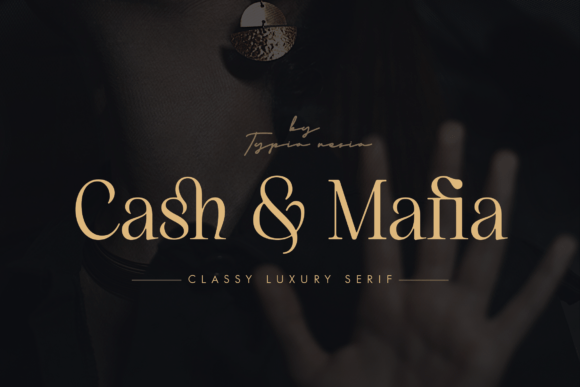
Cash and Mafia
Cash and Mafiaのような高品質の素材をお探しの場合、このプレミアムパッケージはクリエイティブなプロジェクトに素晴らしい選択です。
POD(オンデマンド印刷)製品、結婚式の招待状、またはソーシャルメディアのグラフィックを作成している場合でも、Cash and Mafiaは理想的です。